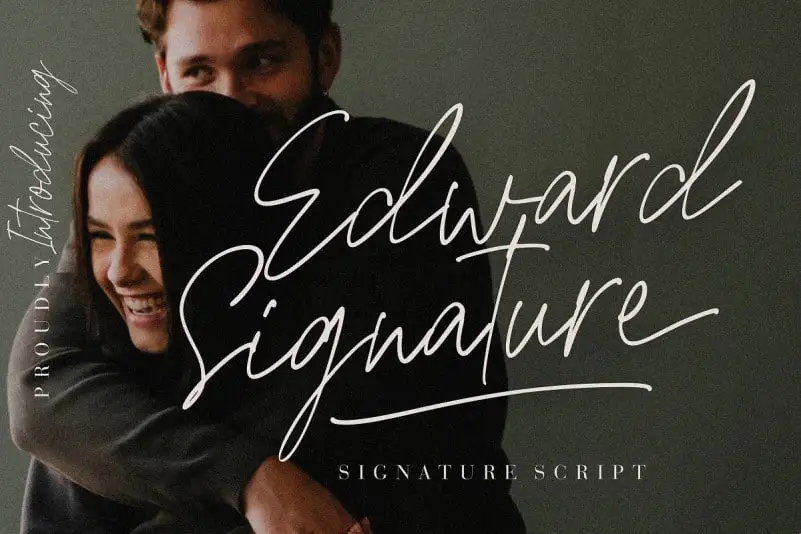
A fonte “Edward Signature Script Font” é uma seleção única para os projetos que valorizam a elegância e a versatilidade do texto manuscrito. Manufacturada pela Creatype Studio, essa tipografia escrita à mão oferece linhas suaves e naturais que transformam qualquer nome ou logotipo em algo refinado e de alto padrão. Seu design está voltado para os projetos de marca, logomarcas, designs de casamento, postagens nas redes sociais, anúncios, embalagens de produtos, designs dos produtos, etiquetas, fotografia, marcas d’água, convites e material gráfico. Não importa o projeto: se ele precisa do sabor da escrita à mão, “Edward Signature” será a escolha perfeita.